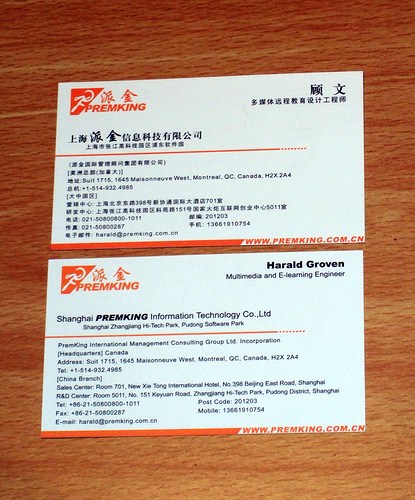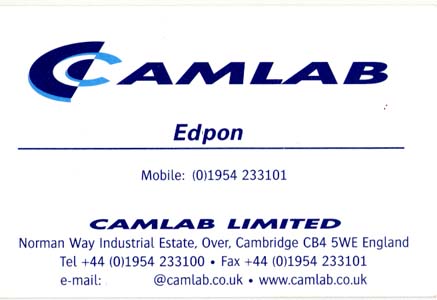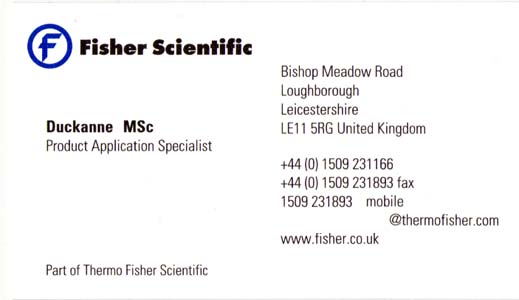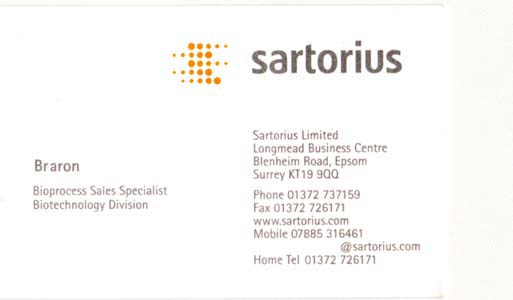
Bei Total Identity gibt es im Moment ein Video, in dem eine interessant gestaltete Visitenkarte gezeigt wird.
Das Ding hat einen Anfangsbuchstaben (Nachname des jeweiligen Menschen?) ausgestanzt. Leider sieht man
das ganze nur kurz und in schlechter Qualität, aber der Film ist generell ganz sehenswert.
scheckkartenformat 85 x 54 mm oder?
meine ist 85 x 50 (bzw. 50 x 85) wo ist das problem?
sehe gerade habe mich vorhin vertippt als ich 80 x 50 schrieb.
aber alle meine vk-bücher-odner etc. die ich habe sind größer
da passen auch karten rein die 90 x 55 sind.
Die Visitenkarten mit den den neuen Kontaktdaten des PBM werden ein Format von 52 mm x 84 mm bekommen. Sandras Argument mit dem Goldenen Schnitt ist einleuchtend. Joh.
Und die brauche ich jetzt. Das ist nicht zu ändern.
Nach Ostern werde ich den großen Herrn und Meister persönlich in mein Magazin einladen - meinen Landlord (Vermieter). Immerhin haben wir in demselben Lehrbetrieb unsere Ausbildung zum Schriftsetzer gemacht, wenn auch mit 25 Jahren Verzögerung. Darüber hinaus wäre es doch gelacht, wenn der mit seinen vielen Druckereien nicht noch irgendwo Bleisatz-Schränke in den Katakomben stehen hat..
Naja und dafür brauche ich die neuen Karten.
Wir sind ja nicht bei Krethi und Plethi, nech?
ber ok markus, mach du doch mal eine.
ich habe mich auch überwunden ;)
Tja, wenn ich die Zeit hätt …
Aber ihr habt eh gemerkt, dass ich mich in der letzten Zeit rar gemacht habe. Bin mit dem Büro umgezogen, habe einige Jobs liegen und versuche dabei mein Weblog täglich mit einem Tipp und wöchentlich mit einem InDesign Video Podcast zu füttern. Meine Abonnierten Feeds kann ich derzeit nur oberflächlich verfolgen.
Mir gefällt übrigens dein Entwurf gut. Er spricht meine Designsprache. Ich würde halt versuchen auf den Auftraggeber im Sinne von weniger ist mehr einzuwirken. Lieber weniger Weissraum und dafür die Infos jeweils so groß als möglich. Eine Visitenkarte sollte man auch nebenher mal zur Hand nehmen können und eine Telefonnummer runter lesen ohne sie einen Meter von der Nase weg halten zu müsse. Ich glaube ›Georg aus dem Blei‹ würde mir zustimmen.
Vielleicht Firma/Privat vorne/hinten. Ich liebe Hochformatkarten. Bei deinem Entwurf finde ich allerdings den unteren grauen Balken etwas zu viel, der Bereich dazwischen wirkt für mich etwas eingeklemmt.
Mit gefielen übrigens auch schon einige, ›ungewöhnlichere‹ Ansätze von zuvor. Ich glaube nicht, dass man sagen kann, das gehört so und so richtig. Man muss sich ansehen wer der Kunde ist, seine Identität erfassen und diese visuell so umsetzen, dass die Zielgruppe damit angesprochen wird.
@ RM: Also, habe mir schnell vor dem Wochenende noch mal die Mühe gemacht und die Karten gescannt. Die sehen natürlich nicht gerade schön aus aber besser gehts halt auf die Schnelle nicht.
Unter den 60 VKs, die hier rumfliegen, finde ich persönlich die Folgende am besten:
Natürlich ist die Schriftgröße zu klein und der Druchschuß zu gering. Aber im Umfeld der anderen Karten funktioniert sie: Das orange Logo sieht man sofort und der graue Text dazu wirkt zumindest auf mich. Durch das grau setzt sie sich vom Rest der Karten ab. Das ist natürlich Teil des CDs; die haben vor einigen Jahren komplett gewechselt und im Großen und Ganzen finde ich es sehr gelungen.
Wenn das CD aber kein Blickfänger ist, dann nützt es eben auch nichts. Ein durchgängig angewandtes CD hat Fisher natürlich auch:
305_fisher_1.jpg
Die Karten sind von der Typografie hier auf dem Schreibtisch besser lesbar als die von Sartorius. Ich überblättere sie aber im Buch gerne. Schwarzer Text auf weißem Grund, dazu ein dunkelblaues Logo, das läßt sich erstaunlich schlecht herauspicken. Es fehlt einfach ein Blickfänger.
Ansonsten sehen die Karten tendenziell eher so aus:
305_camlab_1.jpg
Nach meinem Geschmack ziemlich scheußlich und übersichtlicher oder besser lesbar als die Sartorius-Karte finde ich sie auch nicht, obwohl der Schriftgrad etwas größer ist. Kurioserweise wirkt der fette Schriftzug auf mich überhaupt nicht als Blickfänger im Gegensatz zum orangen Logo von Sartorius.
ich bin neu hier und deshalb erstmal ein „Hallo“ in die freundliche Runde.
Ich bin auf dieses Forum gestossen, weil ich im Moment Visitenkarten gestalte – zwar für mich selbst und nicht kommerziell, aber ich sehe es als Übung (mache seit 08/06 eine Ausbildung zum Mediengestalter).
Ich bin typografisch natürlich noch nicht sehr fortgeschritten, versuche mich aber über die Regeln zu belesen und sie – so gut es geht – anzuwenden.
Die Standardregeln wie die Verwendung von höchstens zwei Schriftarten und die DIN-Abtrennung der Telefonnummern (wobei ich hier auch schon über andere Varianten gelesen habe) habe ich intus, aber das richtige Auge für gewisse Dinge fehlt mir leider. Zum Glück habe ich einen Chef, der gelernter Schriftsetzer ist, und sich sehr gut auskennt, aber meine “Weiterbildung“ fällt meist auf das Wochenende, weshalb ich mich hier etwas informieren möchte/will.
Wenn Du eine Faltkarte daraus machst, fällt die Schräglage in der Gewichtung nicht mehr auf :-)
Laß das Dunkelrot ein paar Millimeter blitzen, das kommt bestimmt gut.
ich finde die Idee super. Das hat richtig was. Ich habe das jetzt mal so umgesetzt – muss allerdings dazu sagen, dass ich enorme Probleme mit der Ausrichten-Funktion von Illustrator habe – aber so geht das wohl jedem in der Lehre. Da hilft nur dran bleiben.
Ich habe die Version mal hochgeladen – hier der Link, weil die Auflösung recht hoch ist.